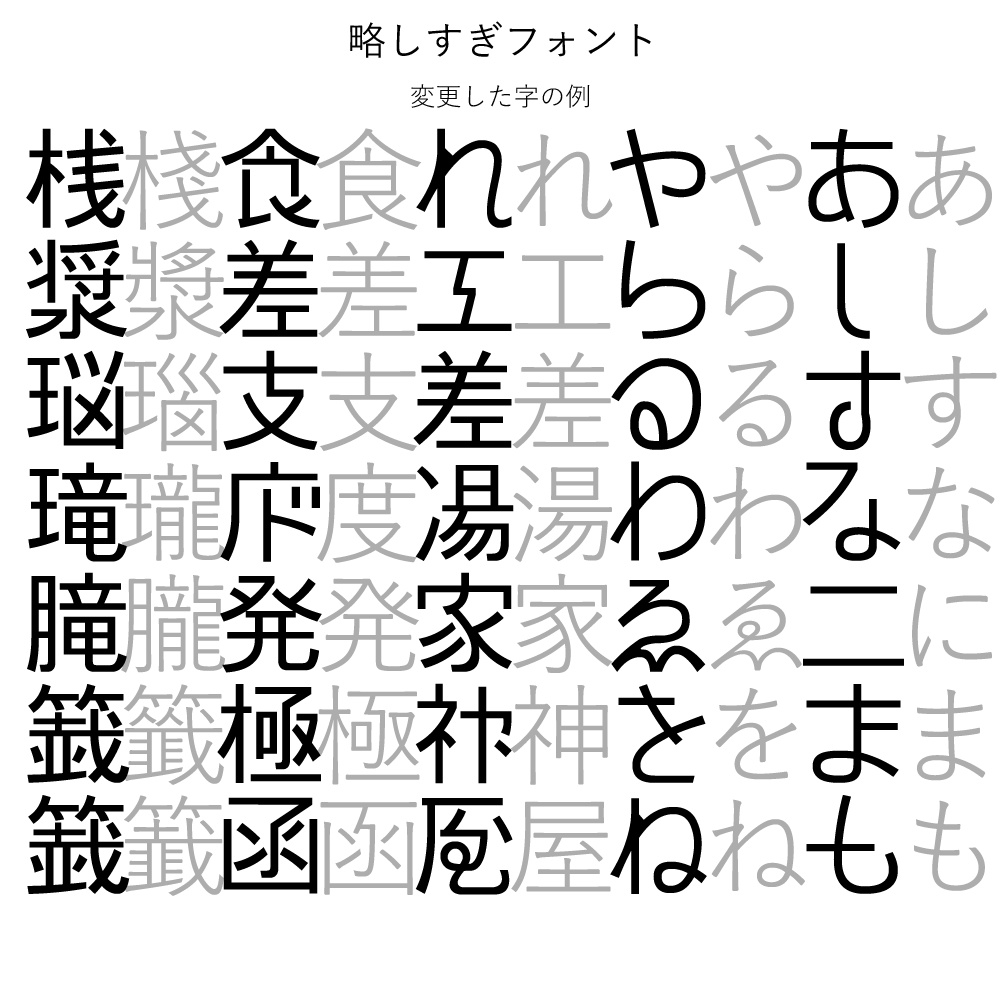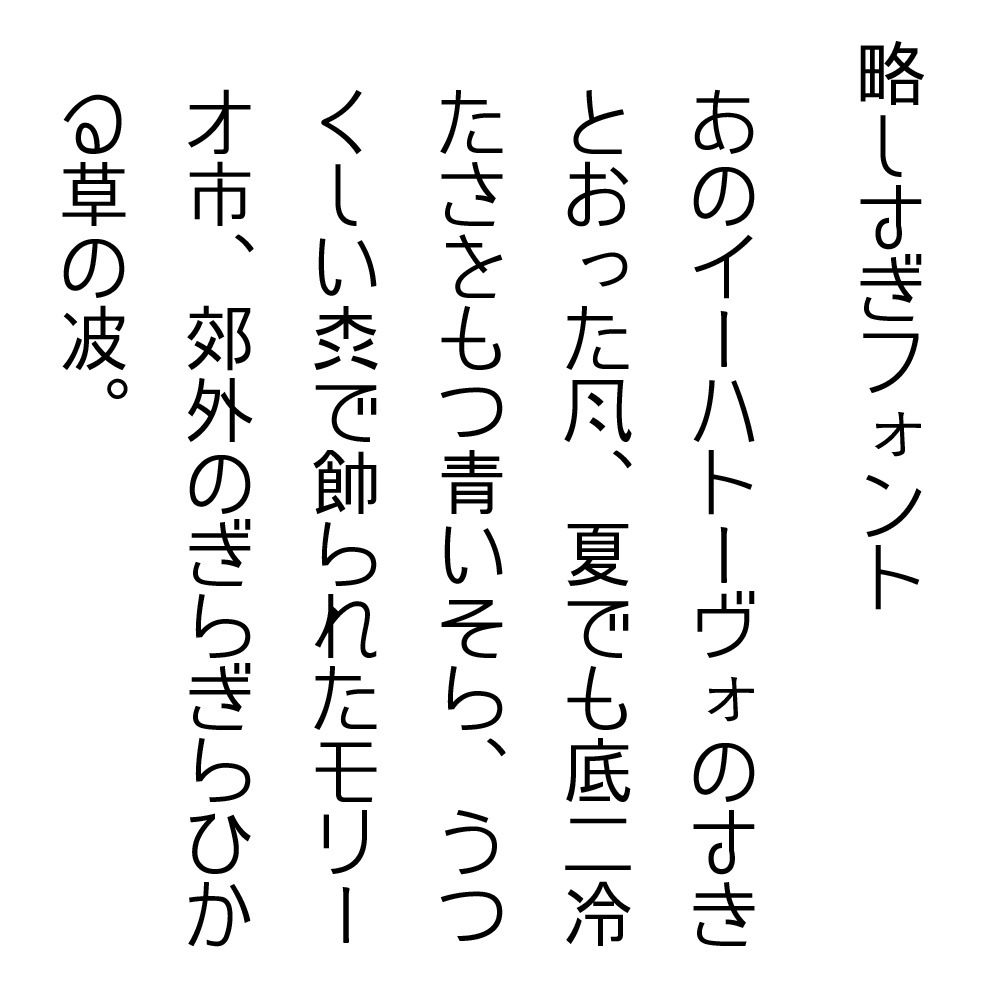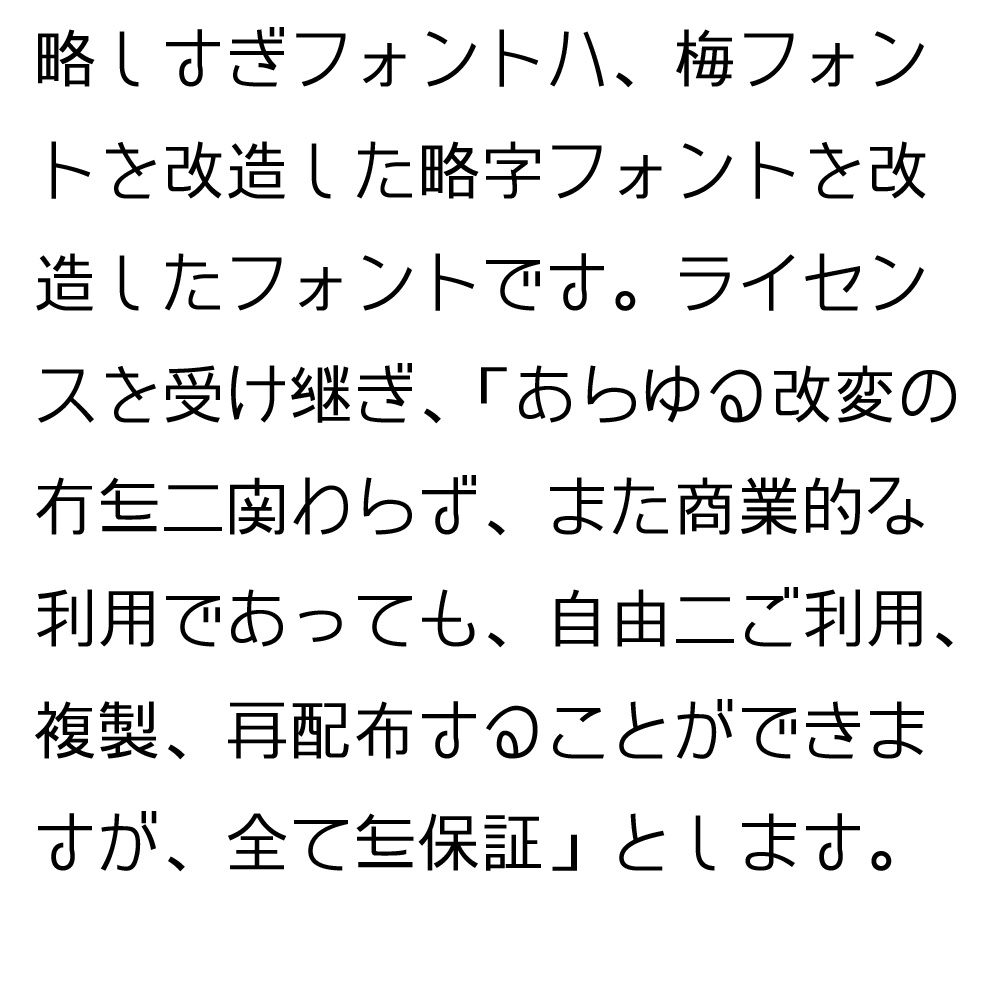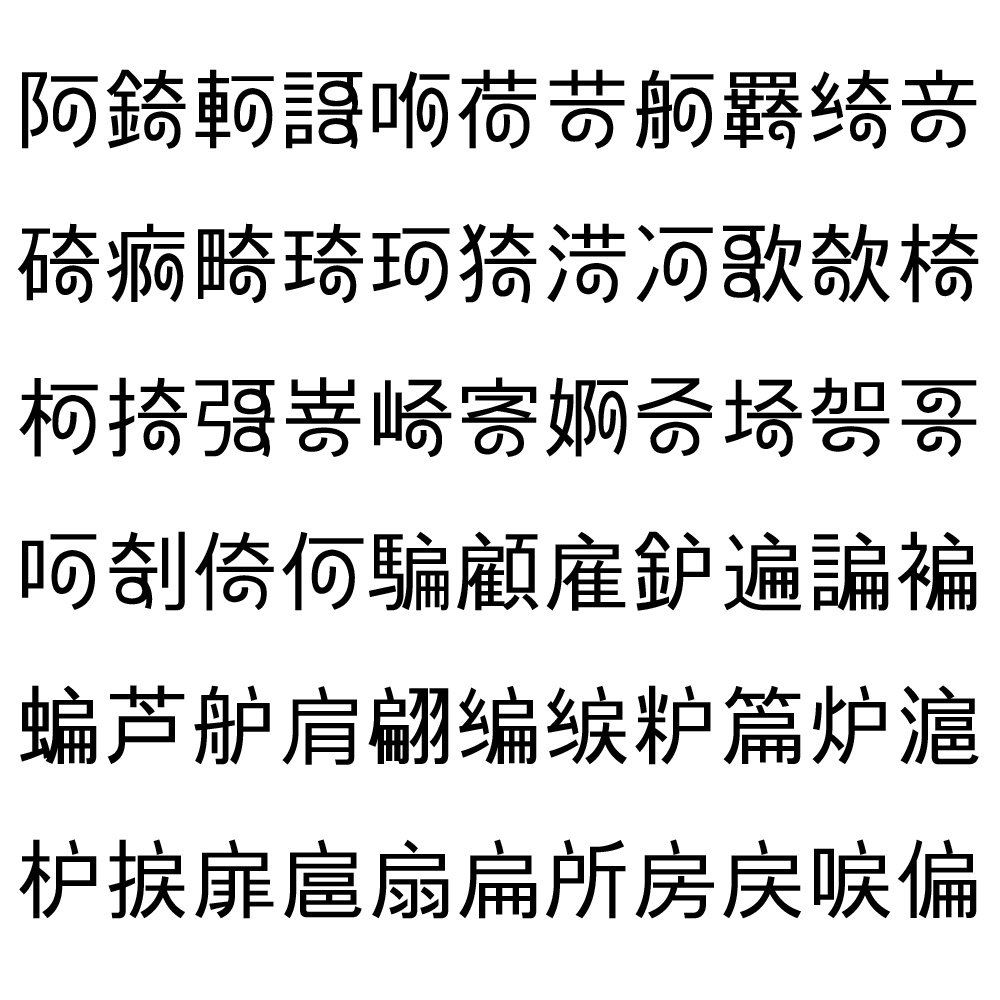
略しすぎフォント
略しすぎフォントは、梅フォントを改造した略字フォントを改造したフォントです。ライセンスを受け継ぎ、「あらゆる改変の有無に関わらず、また商業的な利用であっても、自由にご利用、複製、再配布することができますが、全て無保証」とします。 更新 2019/10/02 戸論 商角微羽 お経の音階の略字から。 将車龍金桂兵 将棋駒の略字 齢齡鴒領零鈴蛉苓聆羚玲澪朎昤怜嶺岺囹冷伶令 「令」を書写体に 2019/05/07 可の略字から類推して阿錡軻謌訶荷苛舸羇綺竒碕痾畸琦珂猗渮河歌欹椅柯掎彁嵜崎寄婀奇埼哿哥呵剞倚何を変更。 漢字の要素に戸を持つ字の手書き字から類推して騙顧雇鈩遍諞褊蝙芦舮肩翩編綟粐篇炉滬枦捩扉扈扇扁所房戻唳偏を変更しました。